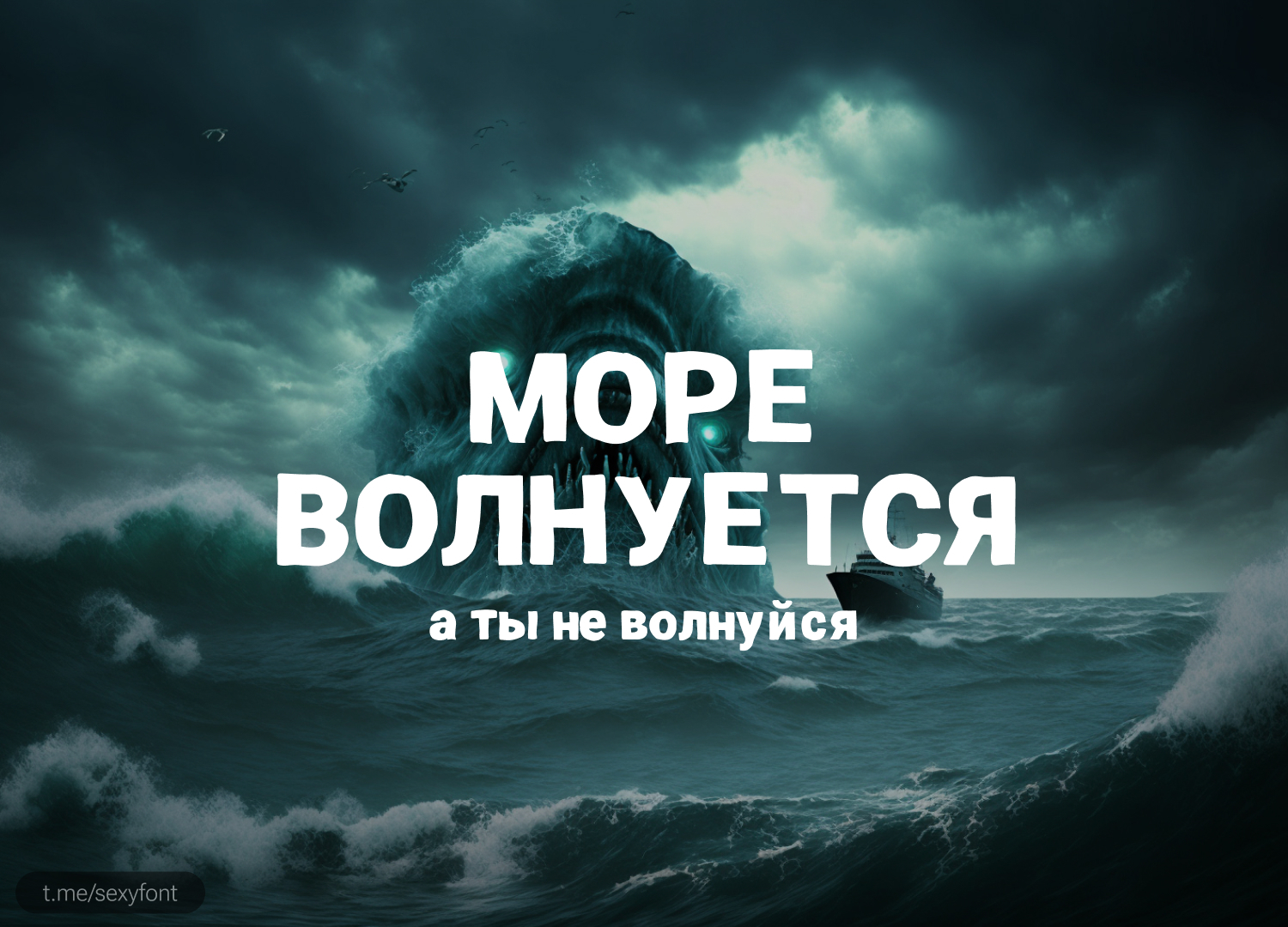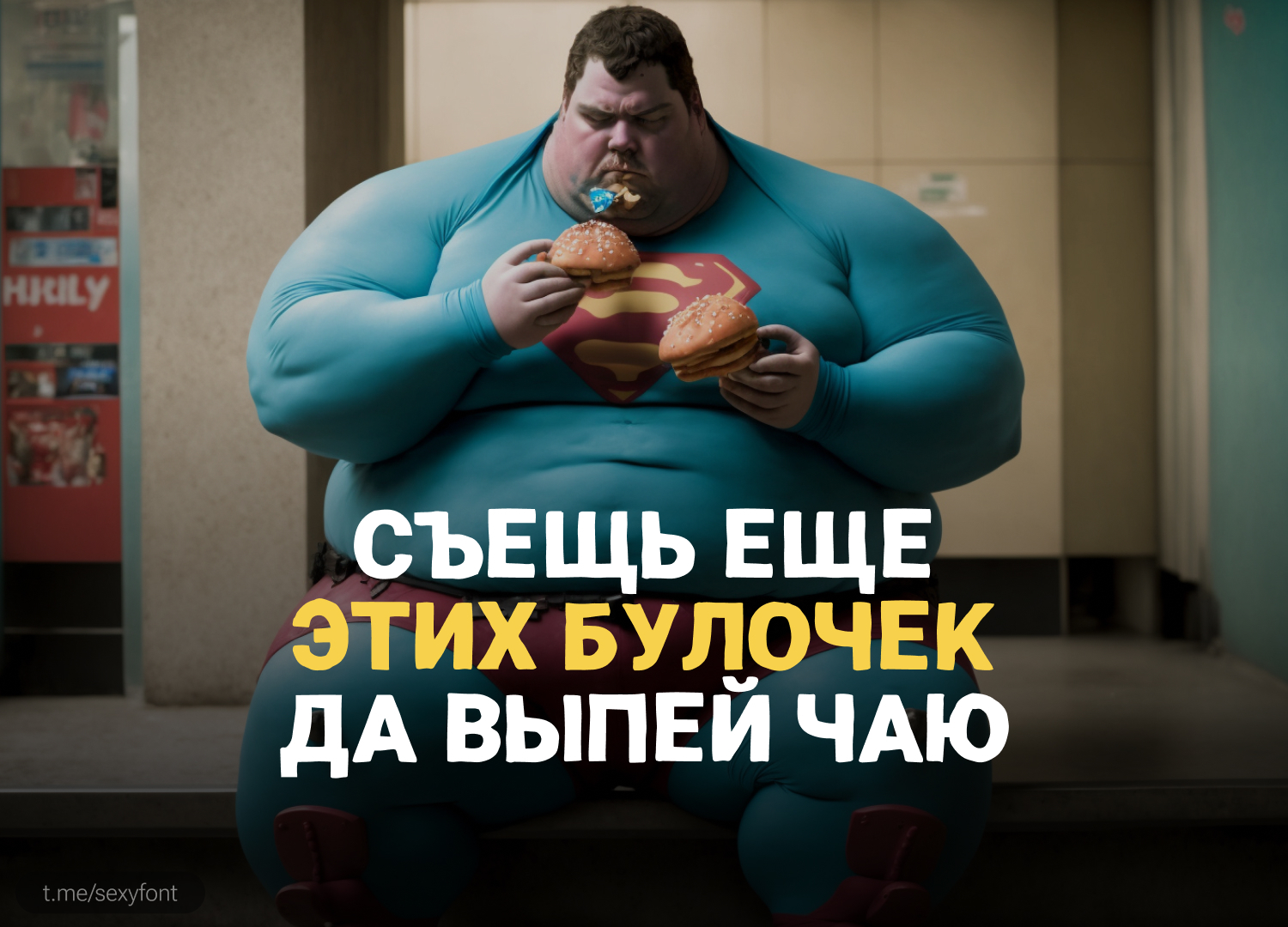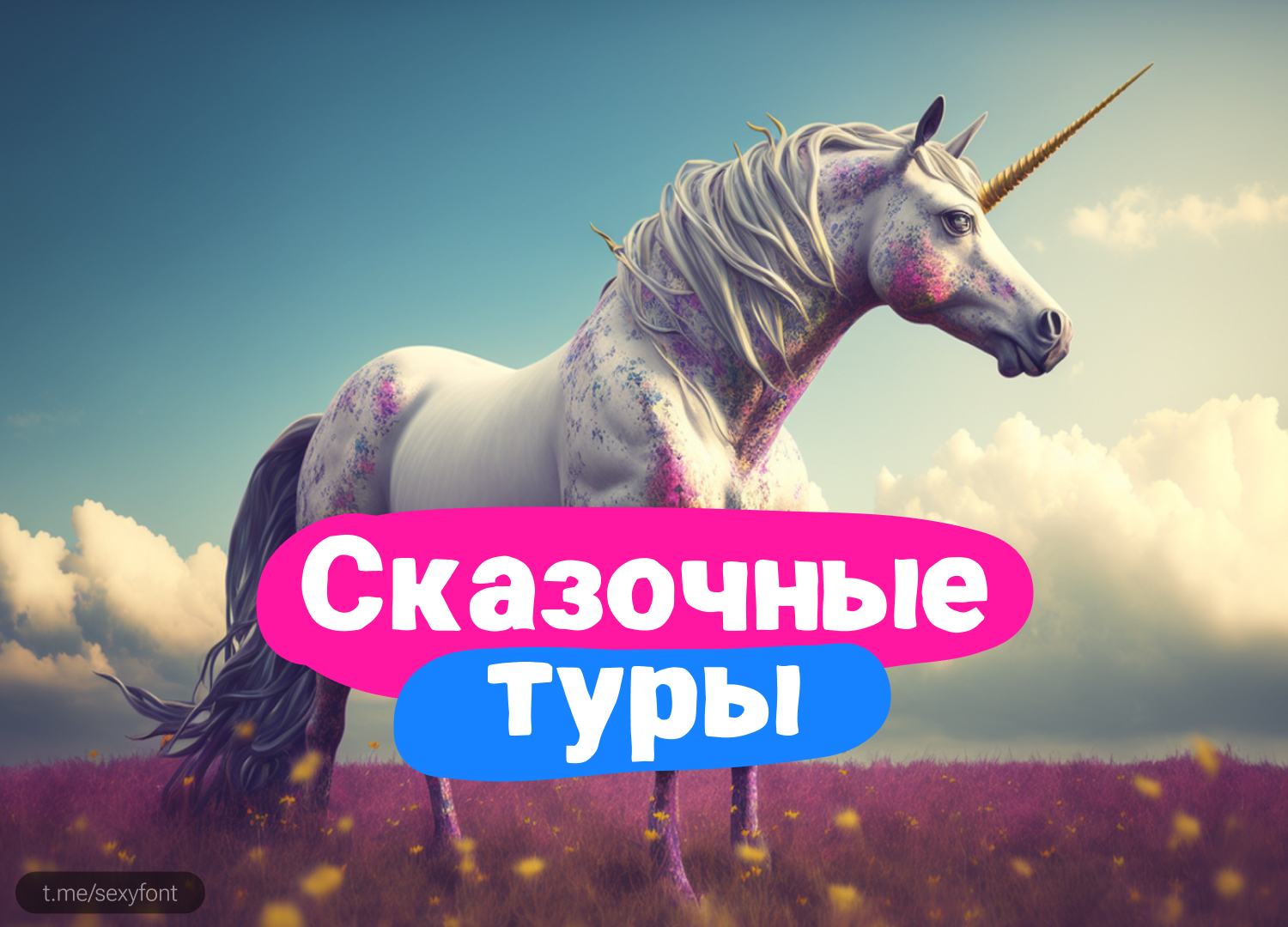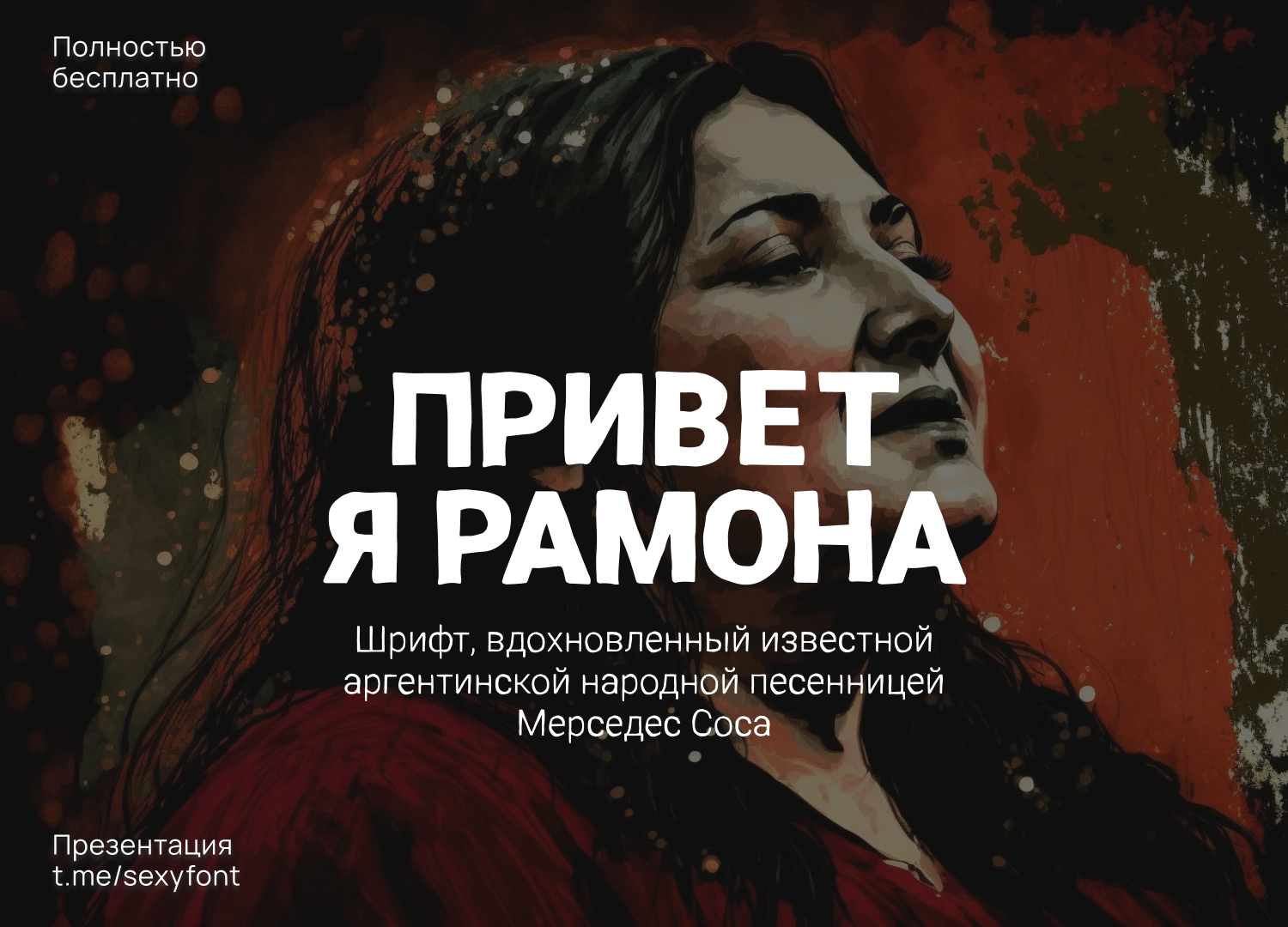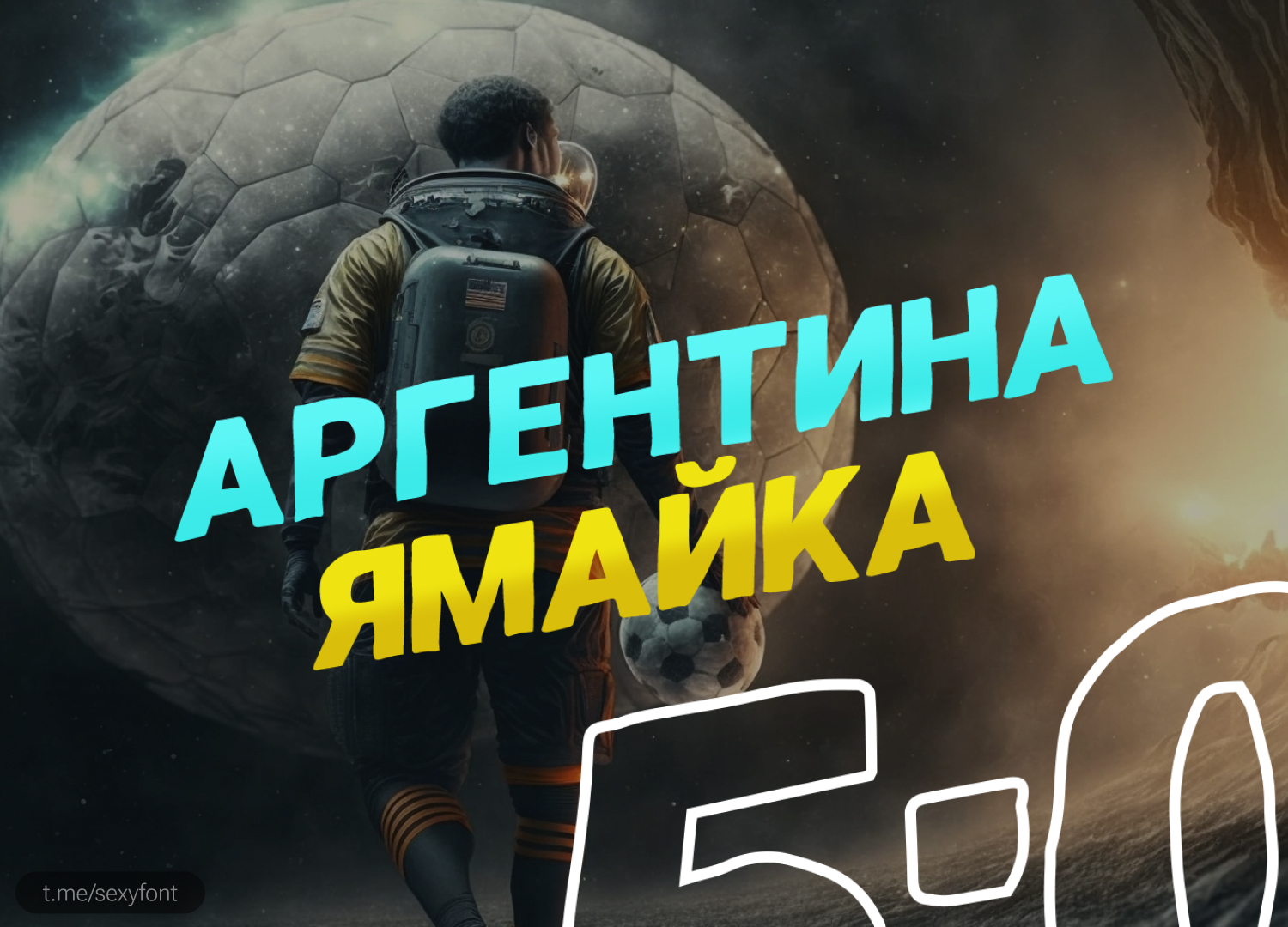
Шрифт Ramona
Идеально подходит для заголовков или основных моментов в плакатах, книгах, журналах, рекламных материалах, рекламе, брендинге или любом тексте, который должен иметь свою индивидуальность. Автор: Аргентинский дизайнер Cristian Tournier